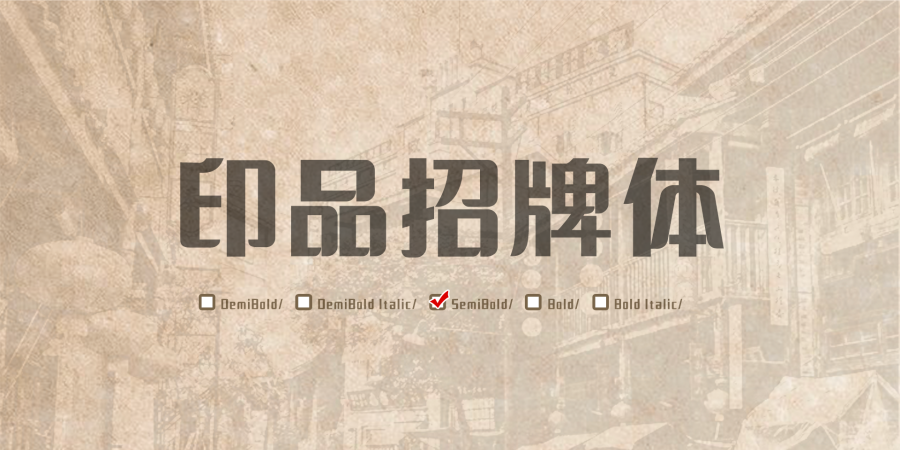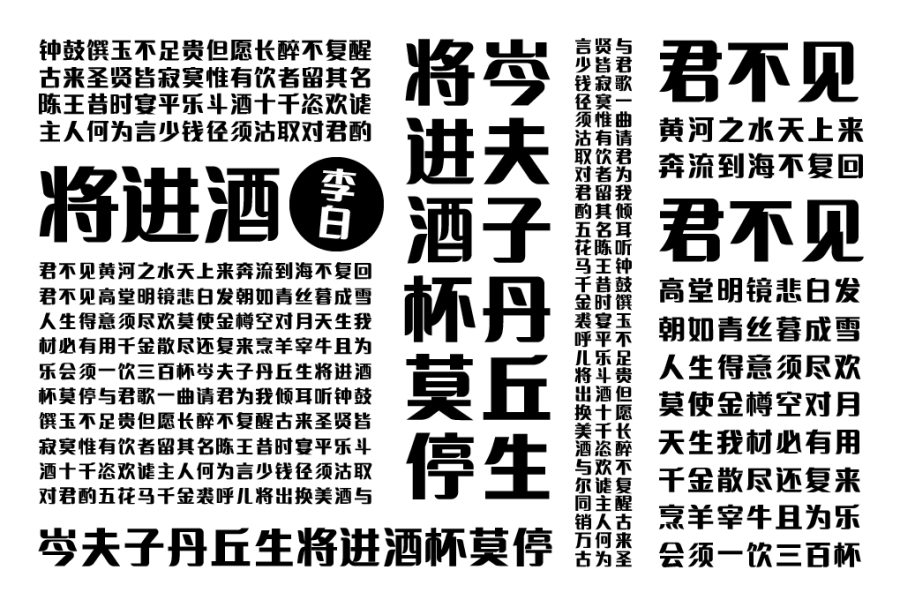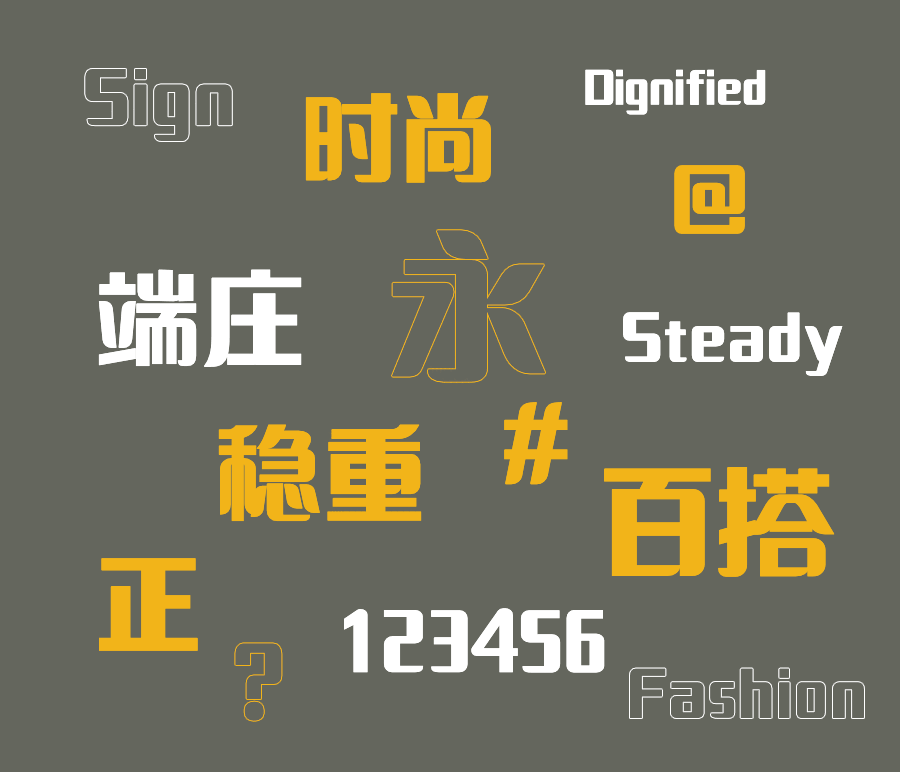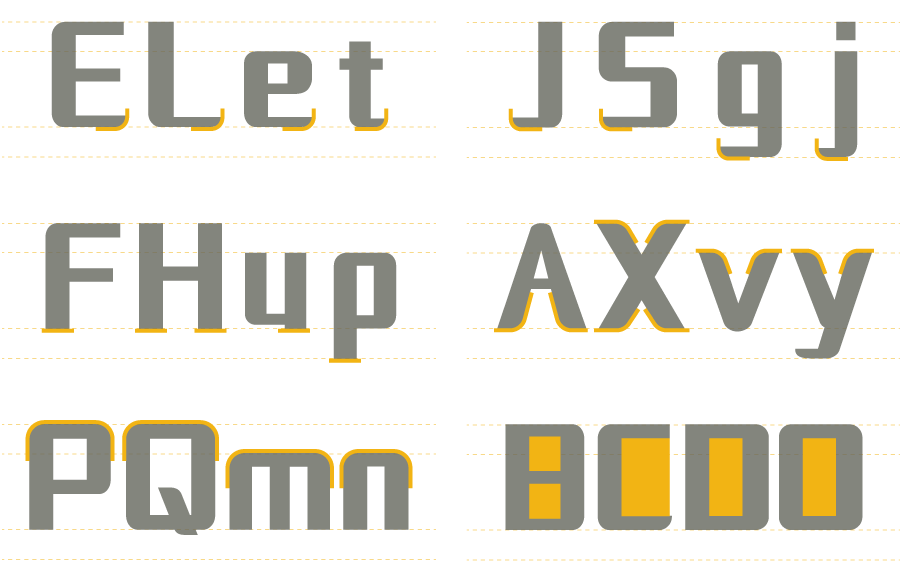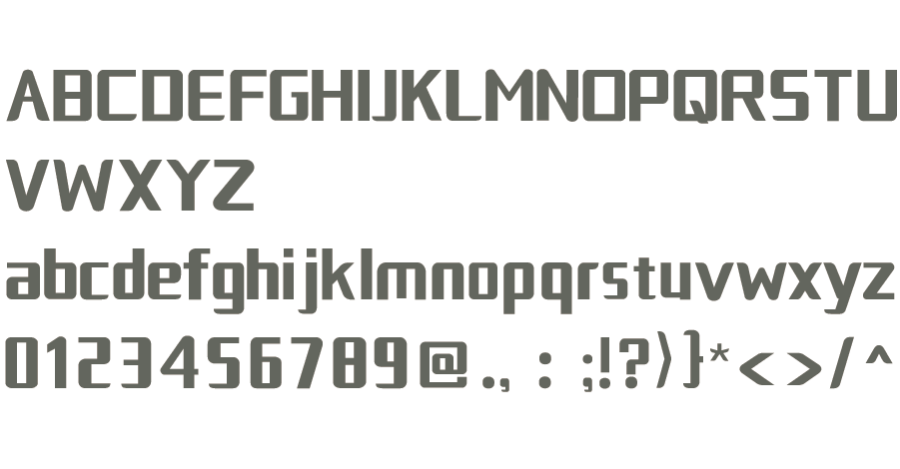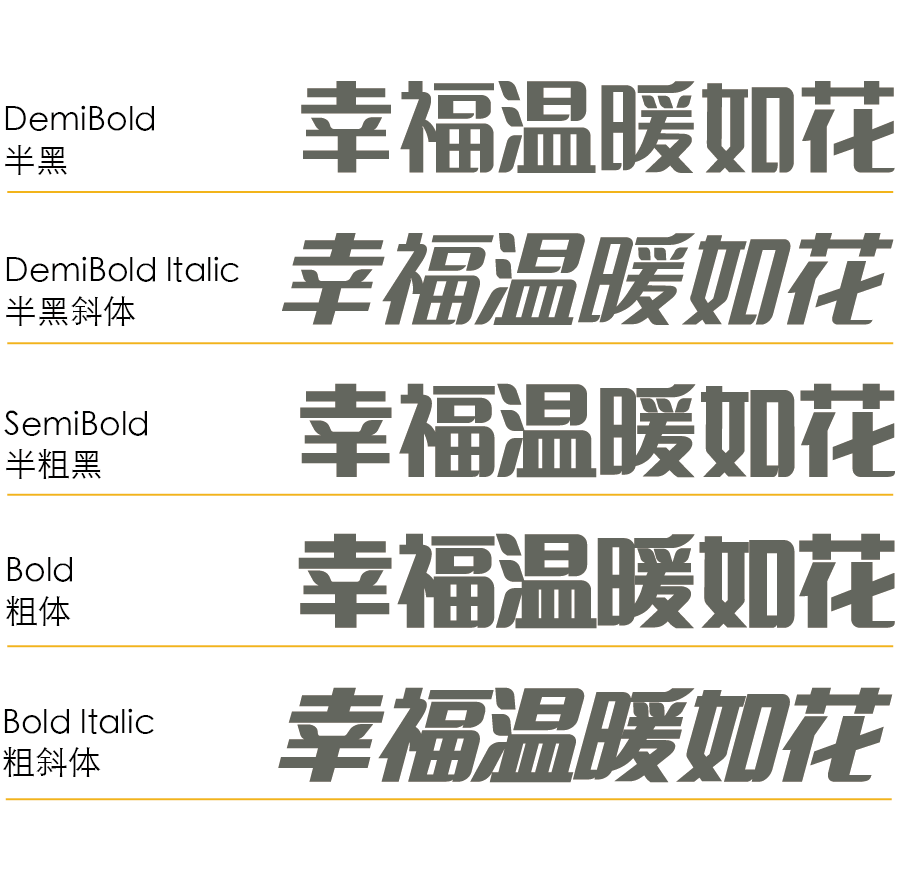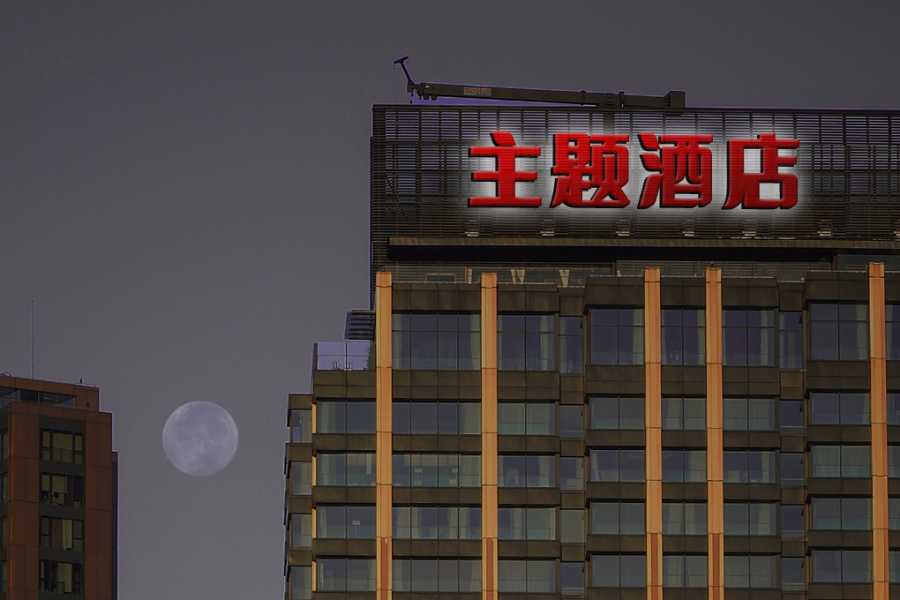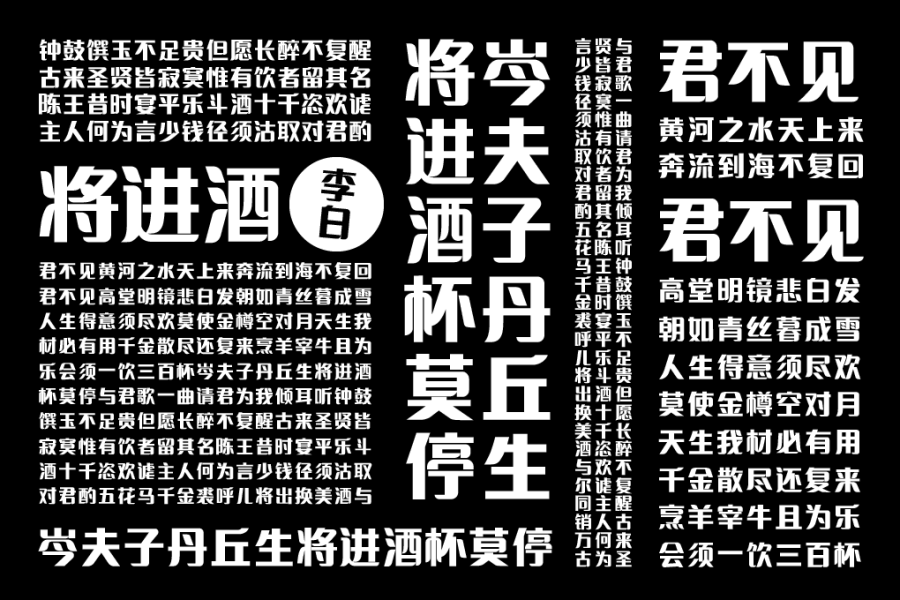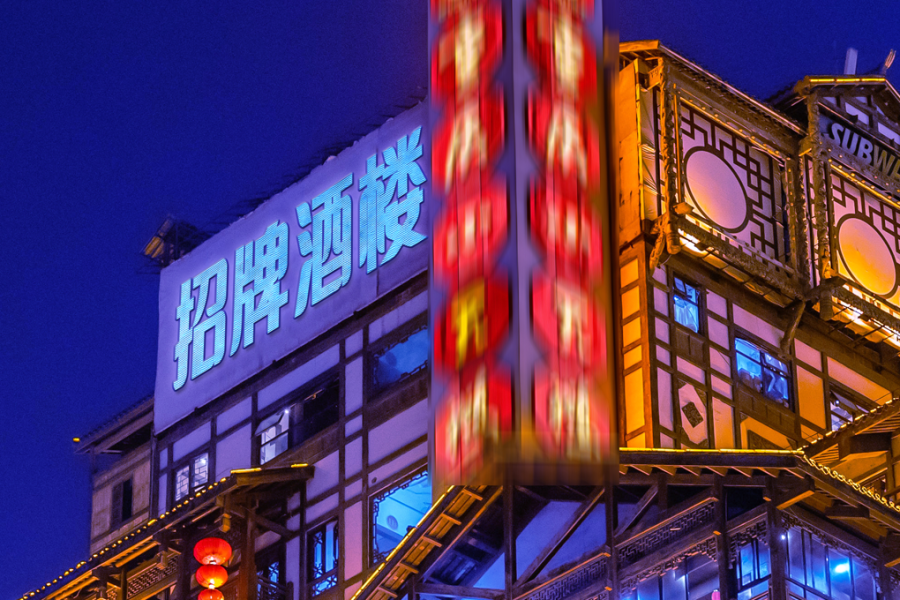
2019年9月在印品清版宋字体刚上线不久,
印品字库/字体视界旗下品牌又推出了一款印品招牌字体,
印品招牌体是一款区别于正文字,适用于招牌的字体。
招牌体适用于少量字数的标题排版设计,
这款字体风格平稳、庄重,适用于书刊封面、商业品牌广告和产品包装设计,
目前这款字体已经正式对外发布。
印品招牌体共收容了7765个字符,其中包含6795个简体汉字,
140个大写字体,159个小写字母,671个其他字符。
笔画介绍
印品招牌体以扁平马克笔的书写轨迹为基础设计,
其外部笔画转折处多为圆弧形,笔形和字形的设计多注重对称均衡。
字体笔画横平竖直,所有口的特点采用了“外圆内方”的设计,
笔锋采用了半圆角设计,外圆角处均为1/4圆角弧度,
整体字体方中带圆,适度收敛,圆润又端庄稳重,刚柔并济。
印品招牌体的西文字样都被固定为统一宽度,在矩形的形状和纵横线之中,
加入了考究的缓和性弧线、圆角以及椭圆形元素。
其中“0”的形状如同显像屏或客机窗框,它蕴藏着单纯几何化的美感,
由此形成一种非常方,缺刚柔并济的单线字体,给文字以现代感和科技感,蕴藏着单纯几何化的美感。
笔画有对称的镜像感
折笔处呈圆弧形,撇捺笔画的起笔与收笔具备柳叶的纤柔感,优美时尚。